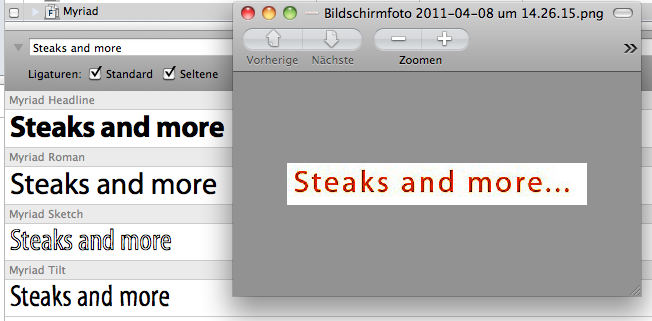
welche schrift ist das?
woher stammt das?
keine ahnung, hab ich mal von irgendeinem logo kopiert. finde nur die schrift cool, aber hab da nix gefunden
ah so, ich dachte das hättest du aus dem www, weil der Dateiname auf einen heutigen Screenshot hinweist.
dachte ich auch schon, das d hat aber eine andere Oberlänge … vielleicht täuscht das auch, ist bei der kleinen Vorlage schwer.